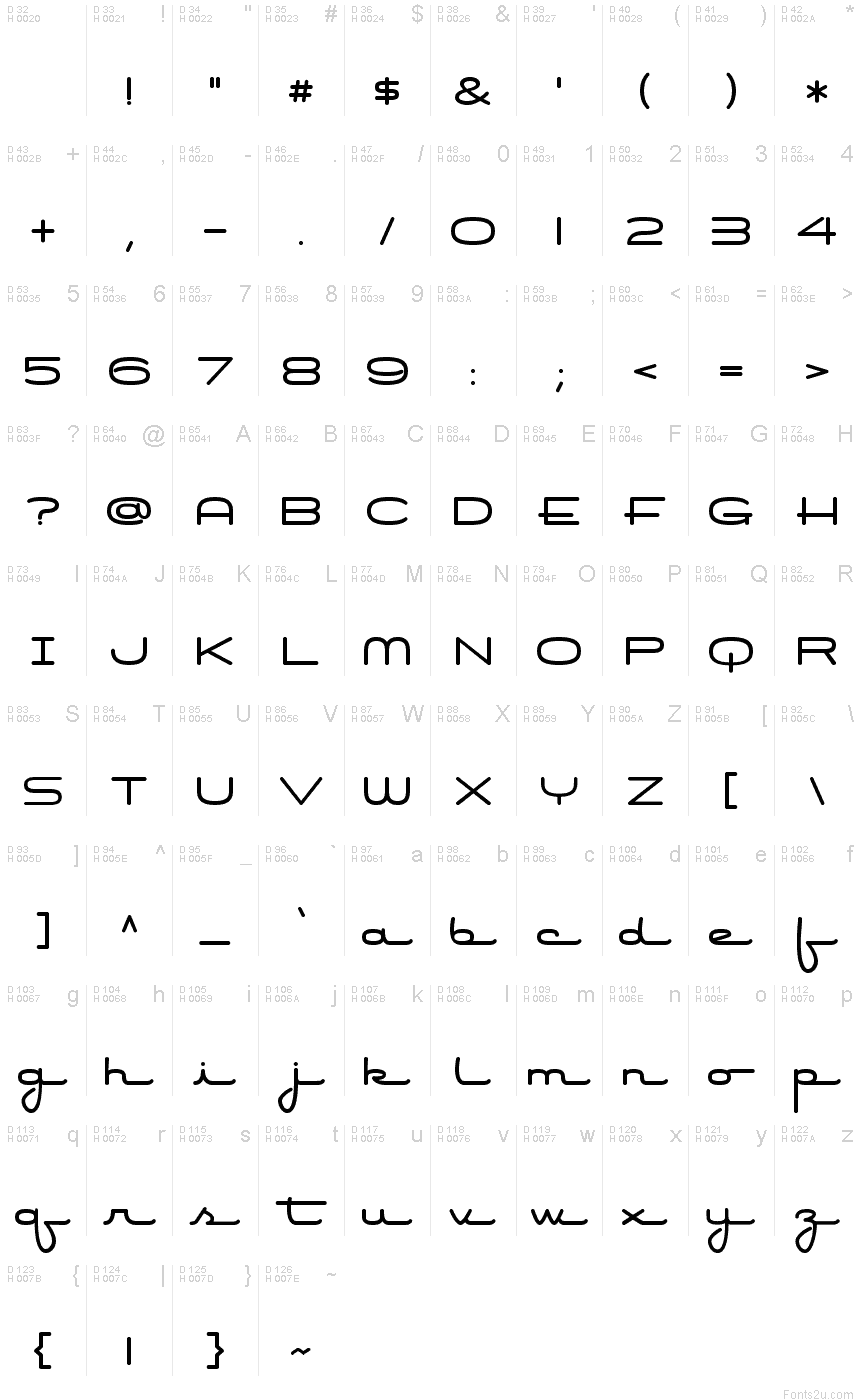
Air Conditioner di Font Diner è un carattere display retro gratuito che ricorda le scritte a mano sulle insegne al neon. I suoi tratti tubolari e avvolgenti scorrono fluidi da una lettera all'altra, donando a ogni parola il fascino disinvolto delle tavole calde di metà secolo. Le forme sottili e il generoso flusso orizzontale danno al testo un aspetto lucido, giocoso e sorprendentemente ordinato.
Air Conditioner è perfetta per menu, branding di gelati o bibite, poster nostalgici, loghi vintage, inviti e packaging retro. Il ritmo delle lettere collegate rende vivaci e slanciate anche le parole brevi, ideale quando serve un titolo con personalità ma senza pesantezza. Abbinala a un carattere sans serif geometrico in maiuscoletto e lascia che Air Conditioner si occupi dei grandi titoli luminosi.